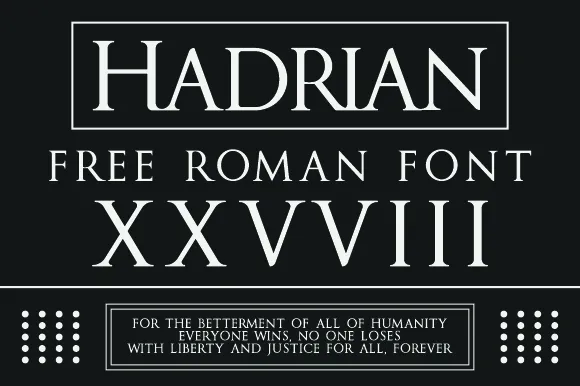
Hadrian Typeface – Download Grátis
A Hadrian Typeface é uma tipografia serifada que combina elegância com modernidade, ideal para trabalhos profissionais onde requisição e sofisticação são fundamentais. Se você aprecia suas linhas perfeitamente regulares e seu equilíbrio harmônico, vale a pena considerar o investimento de um pequeno valor no PayPal para apoiar seus criadores, designers com expertise em detalhes que transformam simples texto em verdadeiras obras de arte. Esta fonte é uma ótima escolha para criar material gráfico requintado e formal, seja para portfolios profissionais ou impressões de qualidade superior.